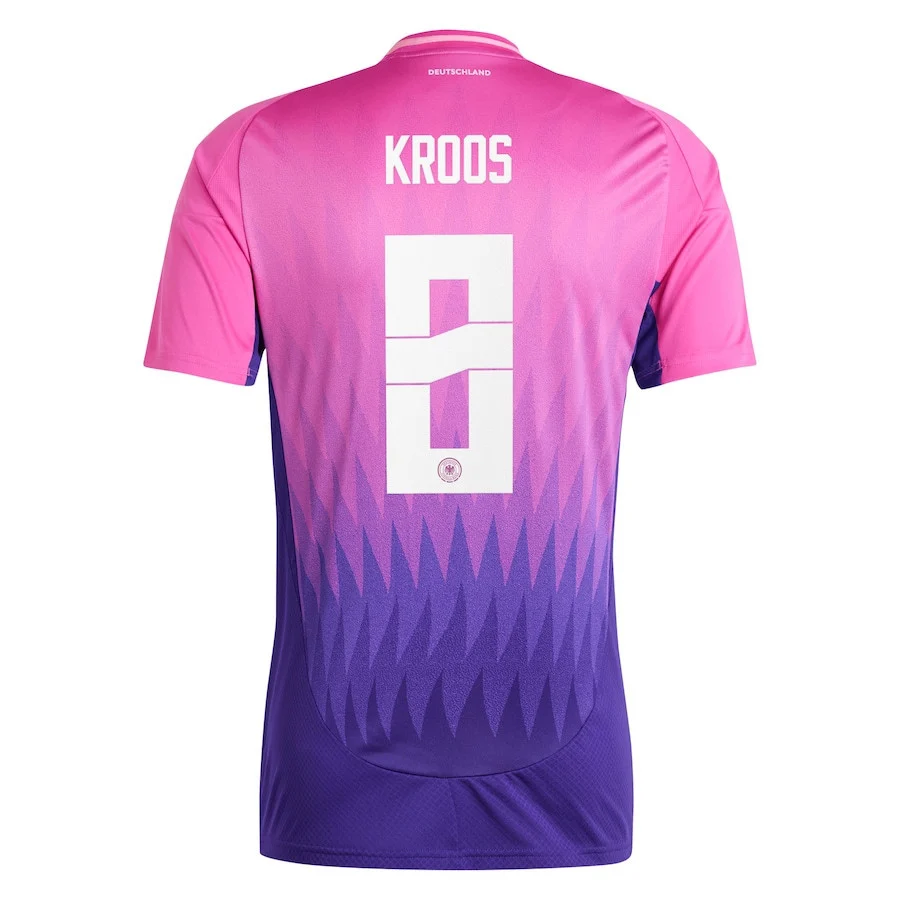
Schriftart auf dem Trikot der Deutschen Nationalmannschaft - EM 2024?
kann mir jemand verraten welche Schriftart auf den Trikots der deutschen Nationalmannschaft verwendet wird? Oder hat jemand ein brauchbares Bild vom Trikot wo man das vielleicht ermitteln könnte? Die bisherigen Versuche haben leider nicht geklappt mit whatdafont und co.
Kein Ahnung. Aber Google hat mir das als Bild geliefert.
Scheint, dass jeder eine eigene Schriftart gewählt hat.
Also wenn ich mir das "R" bei Wirtz und Kroos so ansehe, dann ist das aber dieselbe Schriftart.
Dann ist das 8er oben 'ne Fälschung, fehlt der Schatten/3D
Doch nicht, 1x mit, 1x ohne. Aber ohne die bunten? Irgend etwas stimmt nicht.
Die absolut Originale Schrift unterliegt sehr wahrscheinlich Urheberrechten
Bis auf die Trikotnummer 44, da ist ggf nix drauf 😂